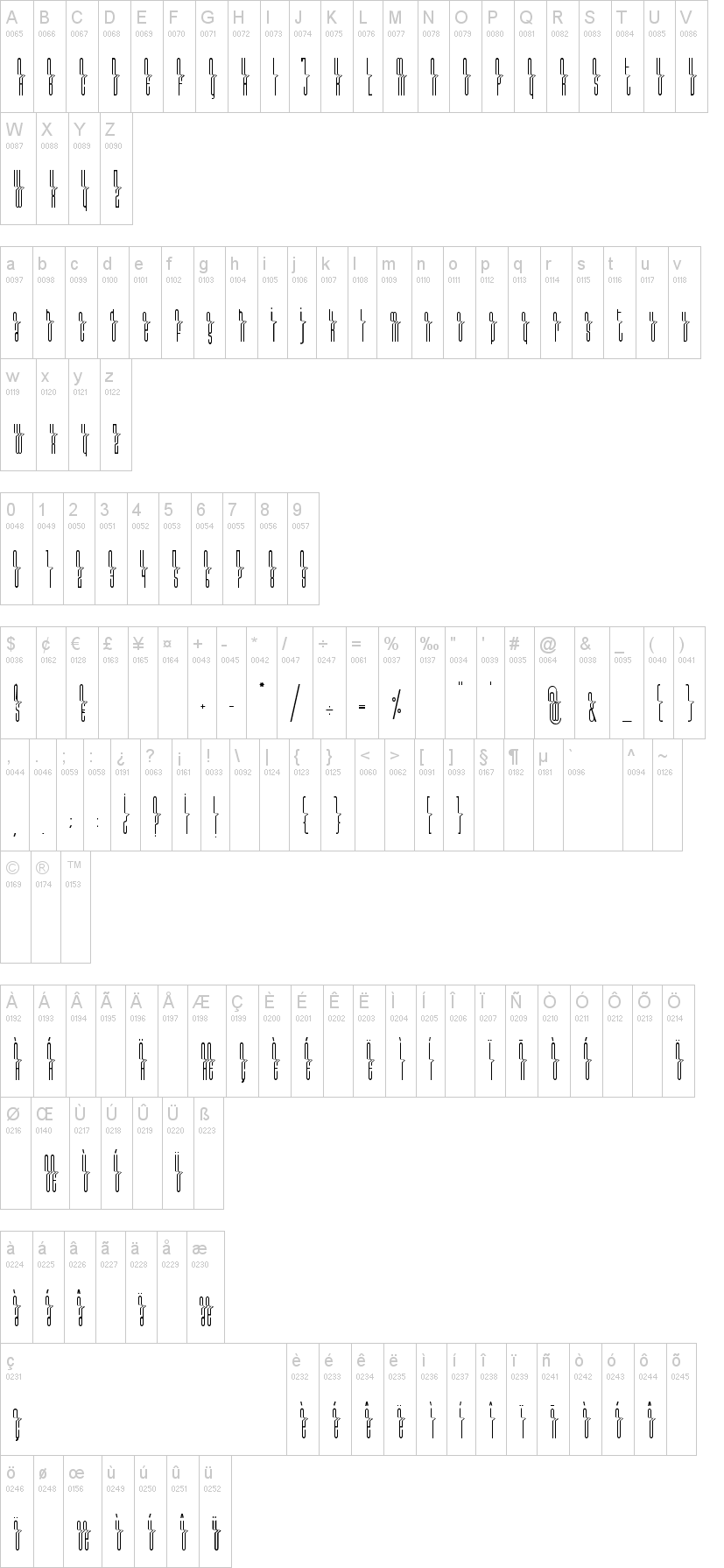
Note of the authorTipografía modular, condensada y experimental basada en el error, concretamente en el desplazamiento de un documento o imagen mientras es escaneado.